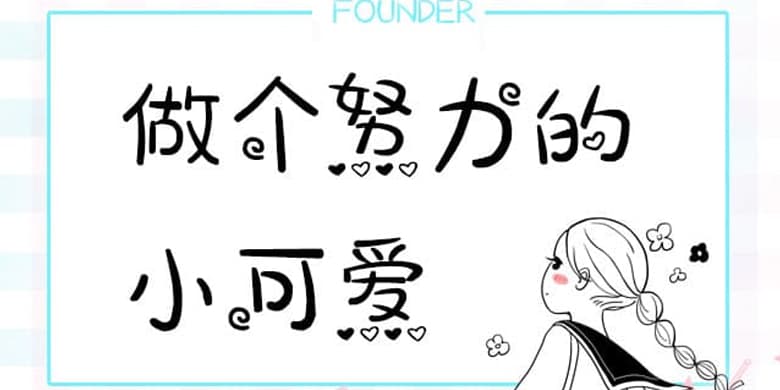
方正手迹-做个努力的小可爱
品牌:方正手迹设计师:俞亦婷发行时间:2020字库编码:大陆简体(GB2312-80)分类:创意书写字体属性:精品字
做个努力的小可爱是一款带着浓烈可爱风的字体,无论是看似胖嘟嘟的字形,还是它圆润的笔画,都在展示她的乖巧俏皮可爱。适用于文艺类的书刊、品牌广告和产品包装设计,以及社交网络的个性化用字。